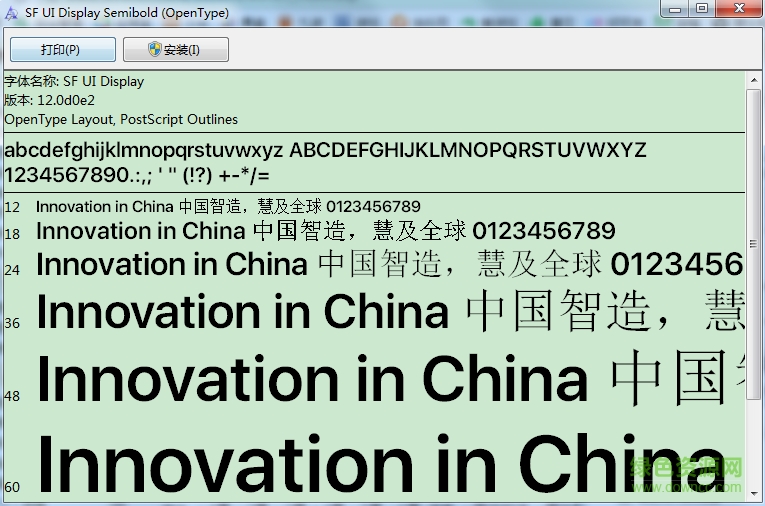
sfuidisplay semibold是一款經(jīng)典的英文字體,這款字體字形簡潔而優(yōu)雅,視覺效果出色,喜歡這款字體的朋友可以來綠色資源網(wǎng)免費(fèi)下載使用喲!
sfuidisplay semibold這款字體秀麗悅目,閱讀性強(qiáng),適合用來文字排版,喜歡就來綠色資源網(wǎng)下載收藏吧!